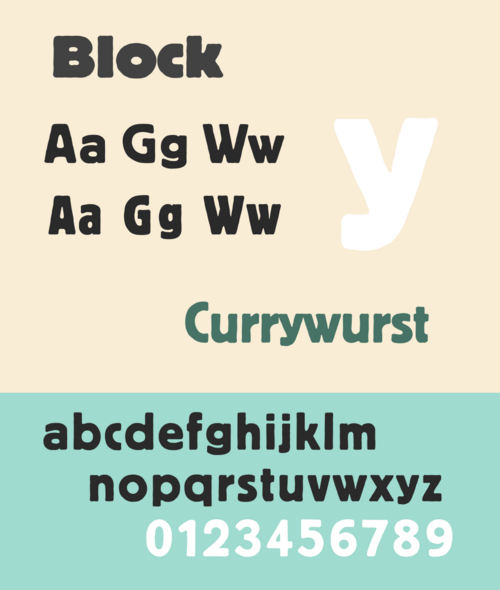
| カテゴリ | サンセリフ |
| デザイナー | ヘルマン・ホフマン |
| 鋳造所 | H. ベルトルト |
| 作成日 | 1908 |
ベルトルド ブロックは、 20 世紀初頭にH. ベルトルド鋳造所から発表された、ディスプレイ用途を目的としたサンセリフ書体です。[ 1 ]ブロックは、見出しに適した太字のデザインで、短いディセンダーにより行間を狭くすることができ、角が丸くなっています。[ 2 ] [ 3 ]単に「ブロック」と呼ばれることもあります。フォントデザインの専門家であるスティーブン コールズは、「コンパクトで有機的な外観を持つ、柔らかくも重厚なディスプレイ書体…本文用ではない」と評しています。 [ 4 ]クリングスポル博物館は、ベルトルドの書体デザインを担当していたヘルマン ホフマンにその功績を帰しています。[ 5 ] [ 6 ]
Block の最初の金属活字版は、使い古された活字の効果に合わせて、意図的に「使い古された」スタイルでリリースされました。一部の再リリース版は、よりすっきりとしたデザインになっています。フェルディナント・ウルリッヒは、これはルシアン・ベルンハルトの作品を含む、当時の広告レタリングの有機的な雰囲気に合わせるためだったと示唆しています。[ 7 ] Block はベルトルトの最も人気のある書体の 1 つです。軽量版や木版 (大判用) など、さまざまなバージョンがリリースされました。[ 8 ]金属活字版には、よりコンパクトな「S」などのスタイリッシュな代替文字があり、書体の外観を微調整し、行に希望の文字数を収めることができました。[ 9 ]
Berthold Blockは1908年にリリースされました。Bertholdは後にウェイトとスタイルを追加し、写真植字版もリリースしました。[ 10 ] [ 11 ] Bertholdはブランド拡張マーケティング戦略として、特に関連性のない他の多くの書体にも「Block」という名前を使用しました。これにはスクリプトフォントの「Block-Signal」とブラックレターのBlock-Frakturが含まれます。[ 1 ]
Block は写真植字の時代にも人気を博し続けました。イェンス・ゲールハールは、「粗い輪郭と太字のウェイトのため、時代を超越したフォントとしては決して候補にはなりませんでしたが、大きな x ハイトとタイトなフィットにより、1970 年代のドイツとイギリスで非常に人気がありました」と述べています。 [ 12 ] 1970 年代と 80 年代には、 Praktikerやホワイトチャペル・アート・ギャラリーがブランディングによく使用しました。 [ 13 ] [ 14 ] 1970 年代後半には、Berthold は Block のデザインから派生した 3 つの軽量フォントをミニファミリー「Berliner Grotesk」として写真植字用に再リリースし、フォントの再描画はErik Spiekermannが行いました。[ 7 ] [ 15 ] [ a ]
Block のデジタル化には、Berthold とその後継会社、 Bitstream (コンデンスド ウェイトのみ)によるものなど、さまざまな種類が存在する。 [ 16 ] [ 17 ] [ 18 ] Paratype of Moscow は 1997 年にキリル文字を含む拡張版をリリースした。[ 2 ] Matthew Butterickの Hermes は、Font Bureauによって最初にリリースされ、後に自主リリースされたもので、同時代の他のドイツのグロテスク書体からも影響を受けた緩やかな適応であり、より軽いウェイトとユニケース機能が追加されている。[ 19 ] [ 20 ]